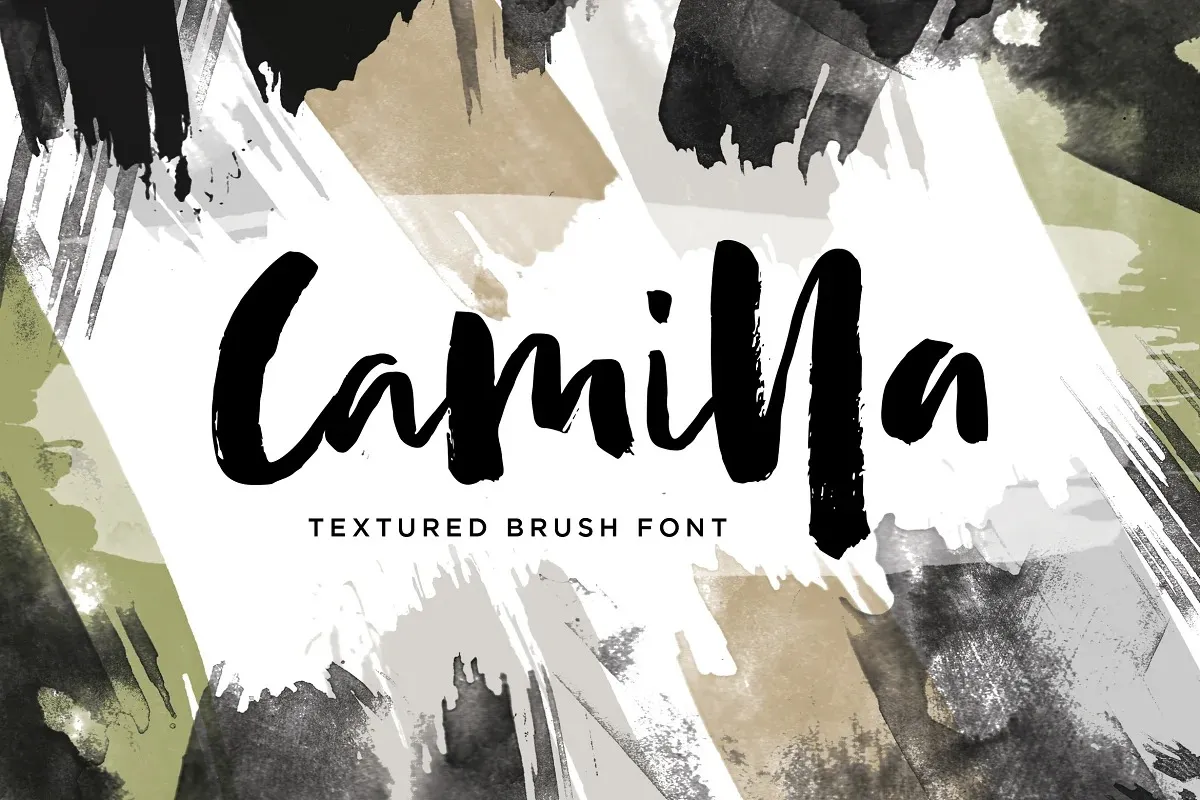
Camilla Font é uma nova fonte moderna feita com açoite, carregada de estilo e abordando design de maneira contemporânea. Desenvolvida e compartilhada pelo Typehand Studio, esta fonte foi criada para parecer naturalmente produzida à mão, ou seja, ela é uma brush font que pode transformar qualquer design em algo deslumbrante ou simplesmente adicionar um toque estiloso a qualquer imagem de fundo. Com seu estilo moderno e sua aparência natural, Camilla oferece aos designers uma maneira incrível de dar vida à suas criações digitais, tornando-as ainda mais atraentes e únicas. Não importa se você está trabalhando em um layout de jornal ou criando um design gráfico complexo, Camilla pode ajudar a destacar seu trabalho com sua elegância única e personalidade vibrante.